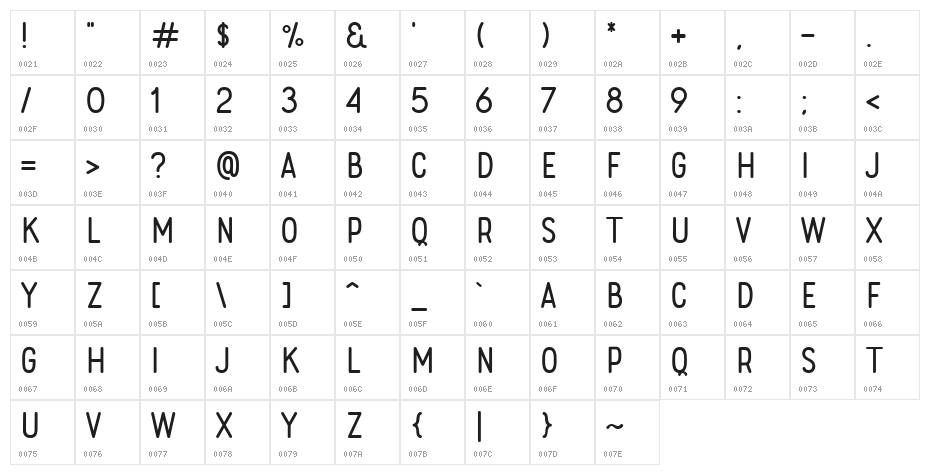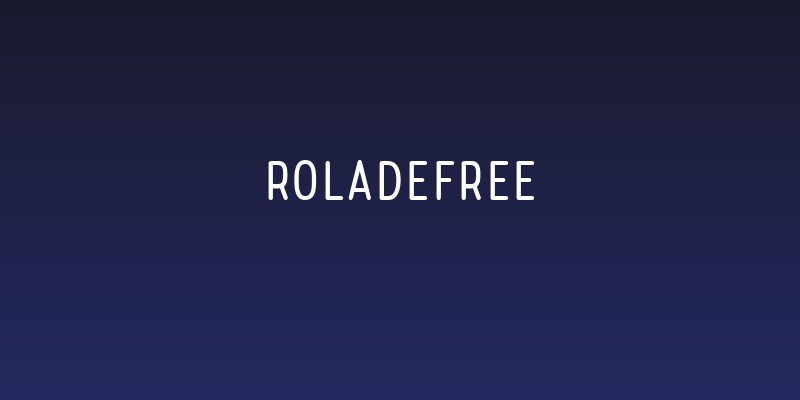
RoladeFree Font
✎ Sans Serif
| Kategorien | Sans Serif |
| Anwendungsfall | Headlines, Body text, Logos |
| Vorgeschlagene Projekte | Ideal for branding, web design, user interfaces, and print materials where a modern and approachable look is desired. |